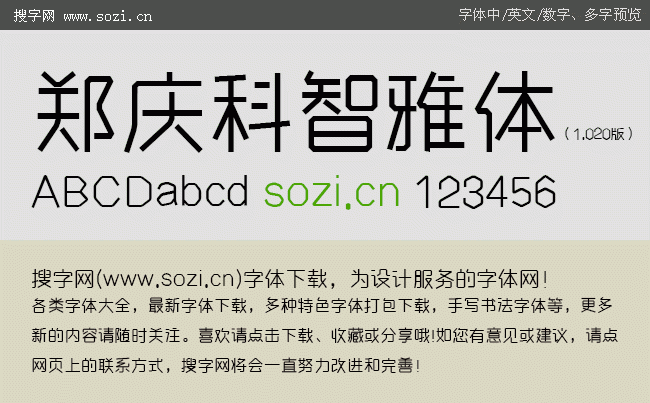
鄭慶科智雅體
搜字網(wǎng)提供一款鄭慶科智雅體字體下載,該字體是基于靜雅體(原時(shí)光體)發(fā)展而來的一款新風(fēng)格字體,典雅大方,字面松緊適中,轉(zhuǎn)角處的特殊處理是其一大特點(diǎn),筆畫全部采用直線處理,柔美而不失剛毅,可以適用于名片設(shè)計(jì)、平面設(shè)計(jì)、廣告設(shè)計(jì)、報(bào)紙雜志、企業(yè)LOGO、商標(biāo)注冊(cè)、電視臺(tái)廣告等應(yīng)用。